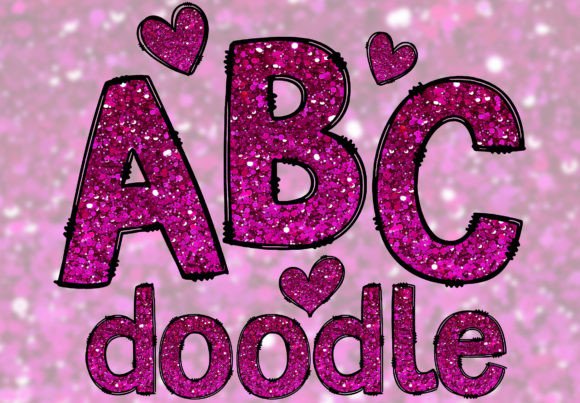
Hot Pink Glitter Doodle Letters PNG
Mencari elemen reka bentuk yang sesuai boleh menjadi mencabar, tetapi Hot Pink Glitter Doodle Letters PNG menawarkan koleksi luar biasa yang menaik taraf karya anda serta-merta.
Dicipta dengan ketepatan, Hot Pink Glitter Doodle Letters PNG menyediakan vektor yang bersih, tipografi yang licin dan lesen komersial untuk ketenangan fikiran.
Sama ada anda mencipta produk POD (Print on Demand), jemputan perkahwinan atau grafik media sosial, Hot Pink Glitter Doodle Letters PNG amat bersesuaian.